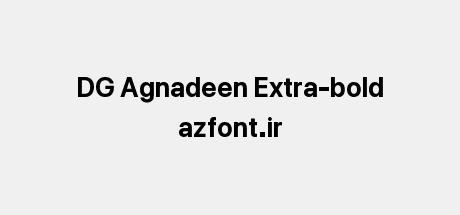
فونت زیبای رایگان DG Agnadeen Extra-bold
قلم زیبای DG Agnadeen Extra-bold از سری قلم های بسیار زیبا برای تایپوگرافی و لوگو تایپ می باشد.این قلم در وزن Regular و توسط https://twitter.com/HossamElNazawy طراحی و منتشر شده است.